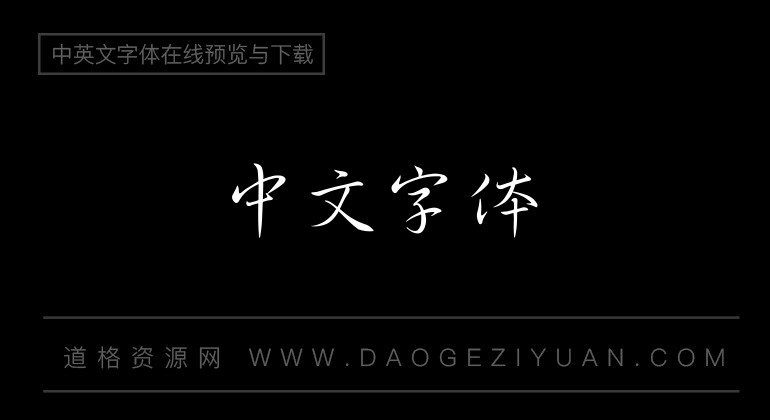
汉鼎简行书
汉鼎简行书是一种简洁大气的行书字体,由中国著名设计师汉鼎先生设计,汉鼎简行书以简洁的行书风格,结合汉字的笔画特色,营造出一种清新的字体美感。汉鼎简行书字体的笔画结构清晰,笔画平行,笔画细腻,字体的结构紧凑,线条流畅,给人一种清新、舒适的感觉。
汉鼎简行书是一款非常不错的手写艺术字体,具有很好的视觉感,适合于文化类的宣传设计、商业类品牌的广告和产品包装设计以及个性化文字排版等较多场景。